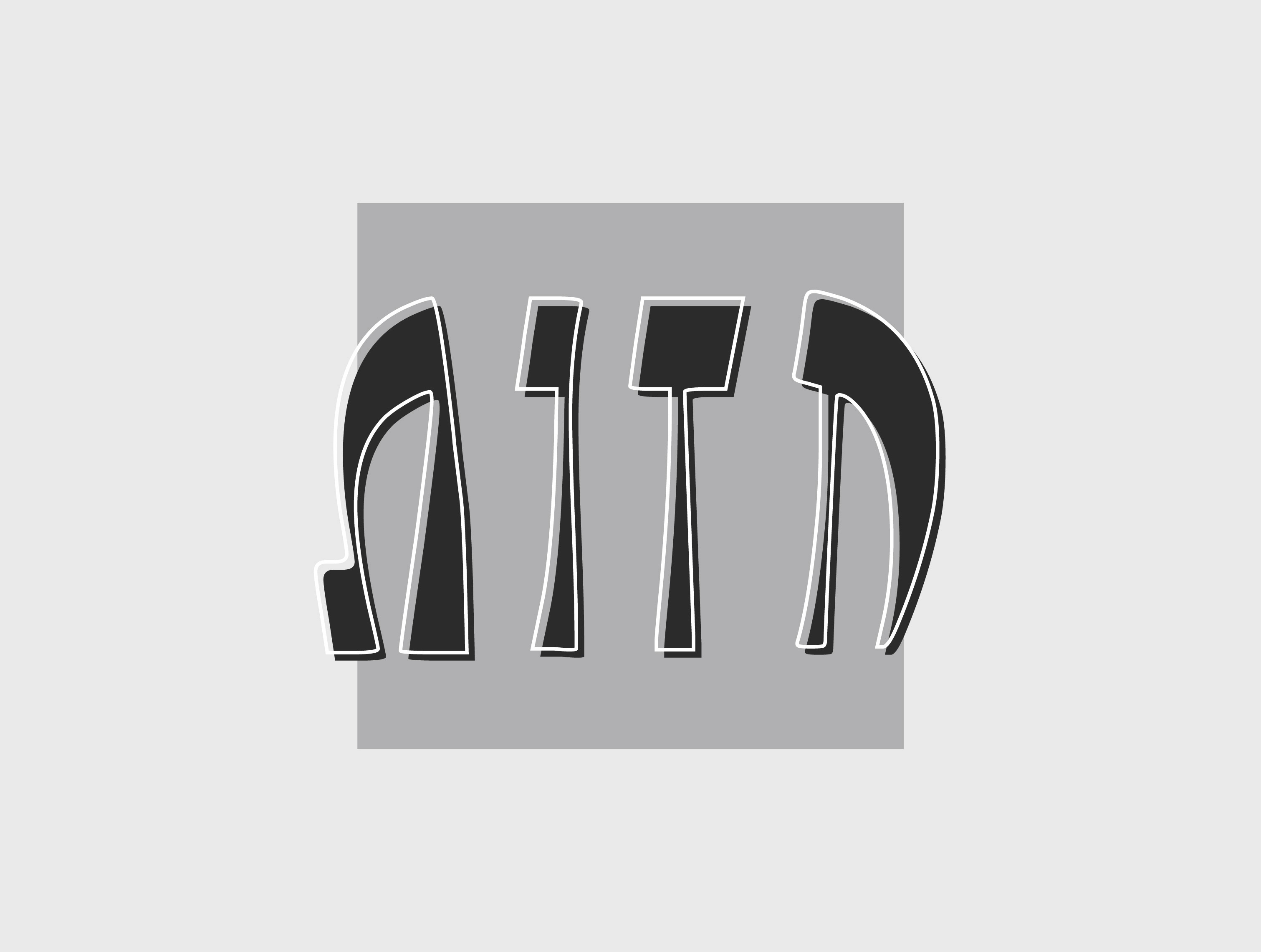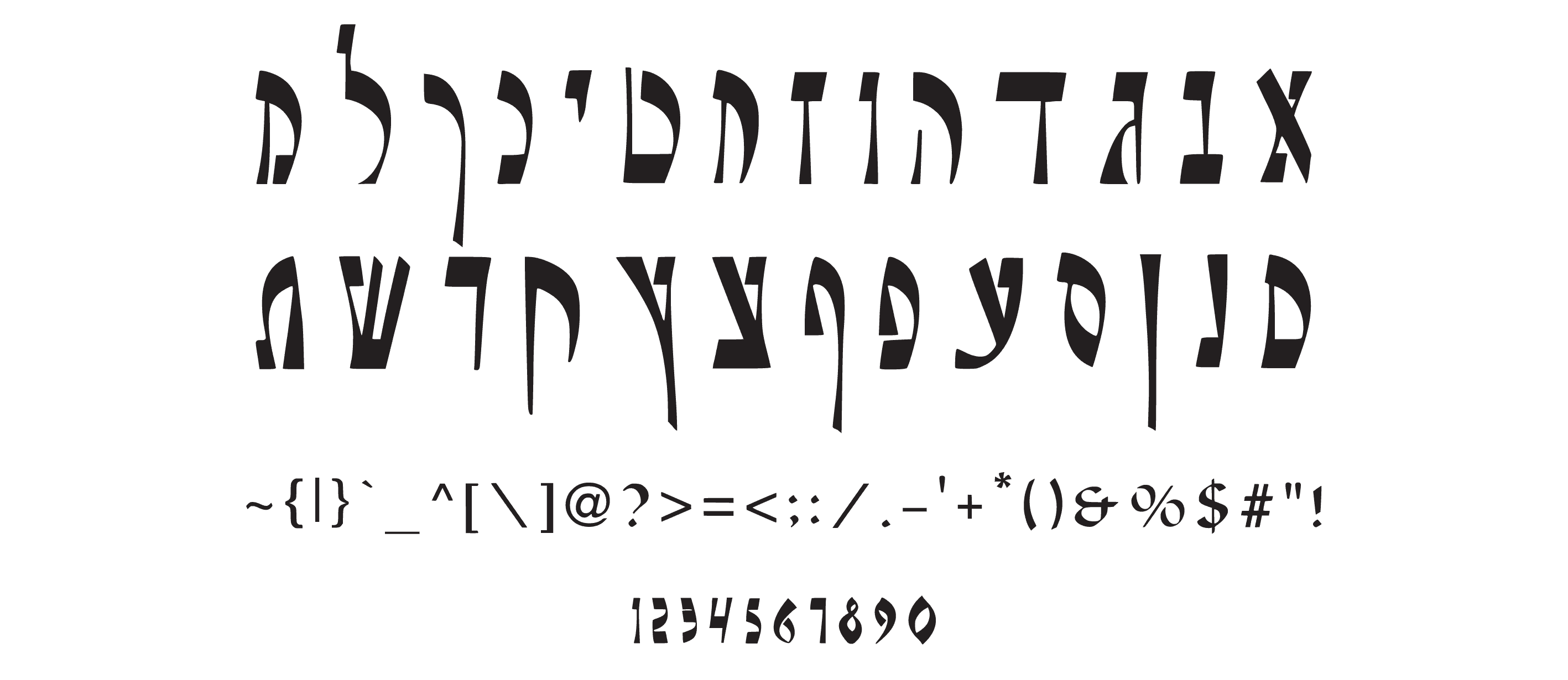
פונט חזות
פונט נועז ובעל נוכחות, עם משחק של קווים חדים ונטייה קלילה — לחוויית קריאה דינמית ומסקרנת.
חזות הוא פונט עברי ייחודי שמשלב בין קווים חדים לתנועות עגולות. החיתוכים הדרמטיים מעניקים לו מראה אסרטיבי ובולט, שמזכיר שלטי ניאון או פוסטרים רטרו-עתידניים.
הוא מתאים למגוון רחב של שימושים גרפיים:
מיתוג נועז
פוסטרים ואיורים
עטיפות ספרים
לוגואים דינמיים
כל פרויקט שדורש טוויסט דרמטי
פונט חזות נוצר מתוך רצון לאתגר את גבולות הקריאות תוך שמירה על נוחות עין גבוהה.